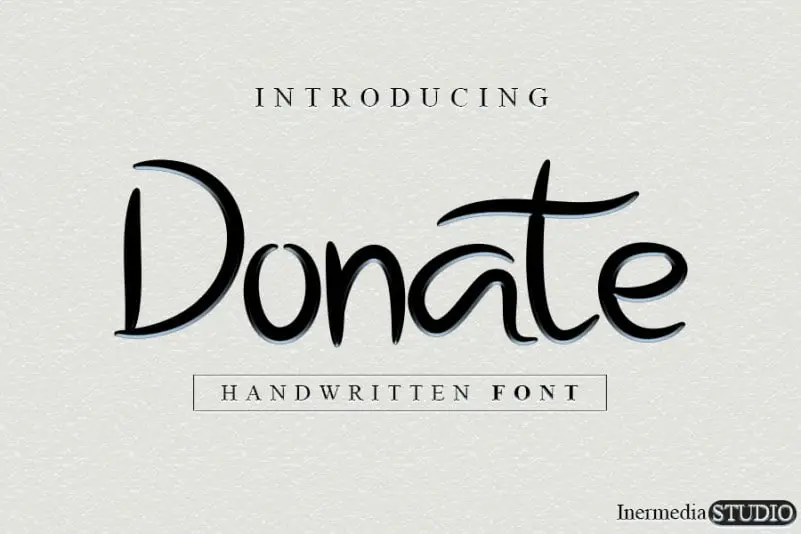
Donate Display Font – Download Grátis
A fonte “Donate Display Font” é uma escolha perfeita para quem busca algo divertido e diferente no seu próximo projeto visual. Embora se baseie nas influências clássicas do estilo de caligrafia, a “Donate Display Font” traz uma sensação contemporânea e atual que certamente irá impressionar. Com sua versatilidade, ela atende perfeitamente para diversas aplicações, desde os cartões de apresentação até os nomes em grandes letras ou material de embalagem. Este design de fonte, criado pelo inermediaSTUDIO com um estilo leve e divertido, é ideal para quem quer dar uma pitada de alegria sem sacrificar o aspecto elegante de um texto impresso. Seja você designer gráfico ou simplesmente alguém que adora criar coisas bonitas, a “Donate Display Font” certamente vai tornar seu trabalho mais agradável e único.